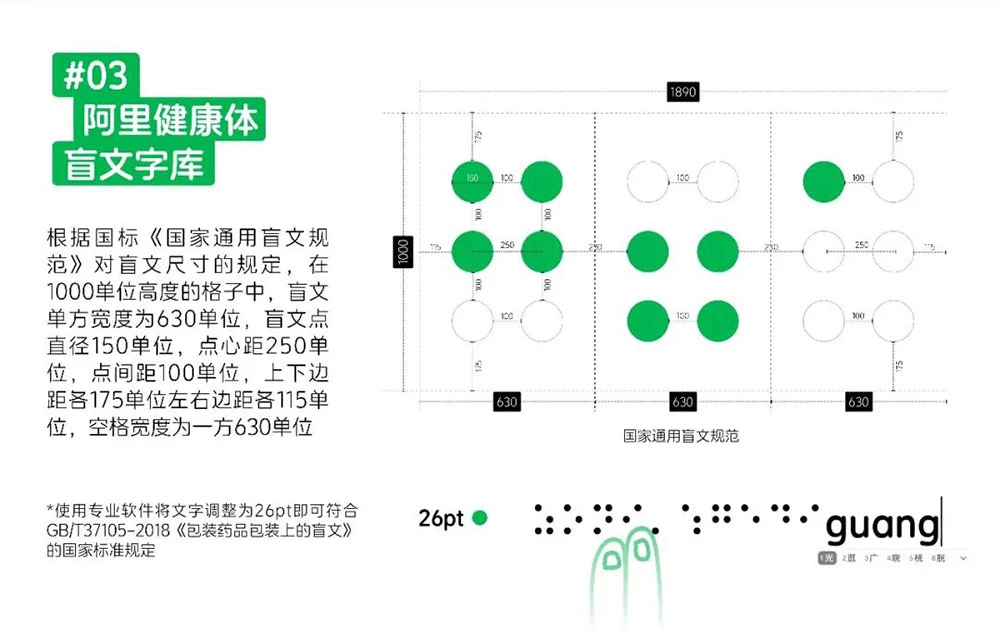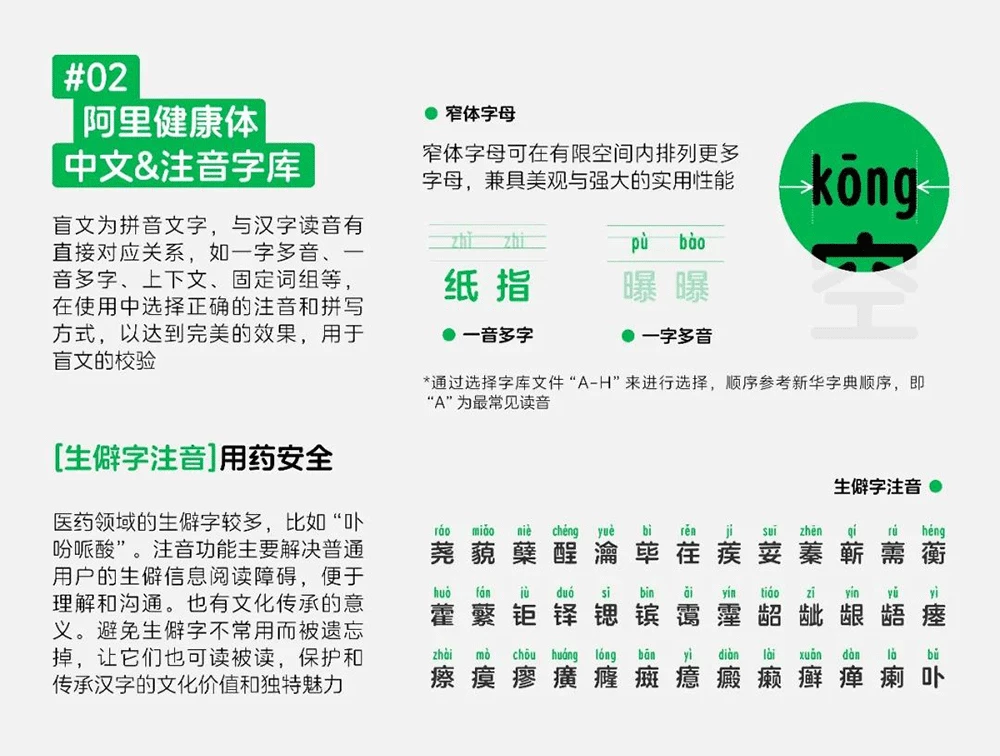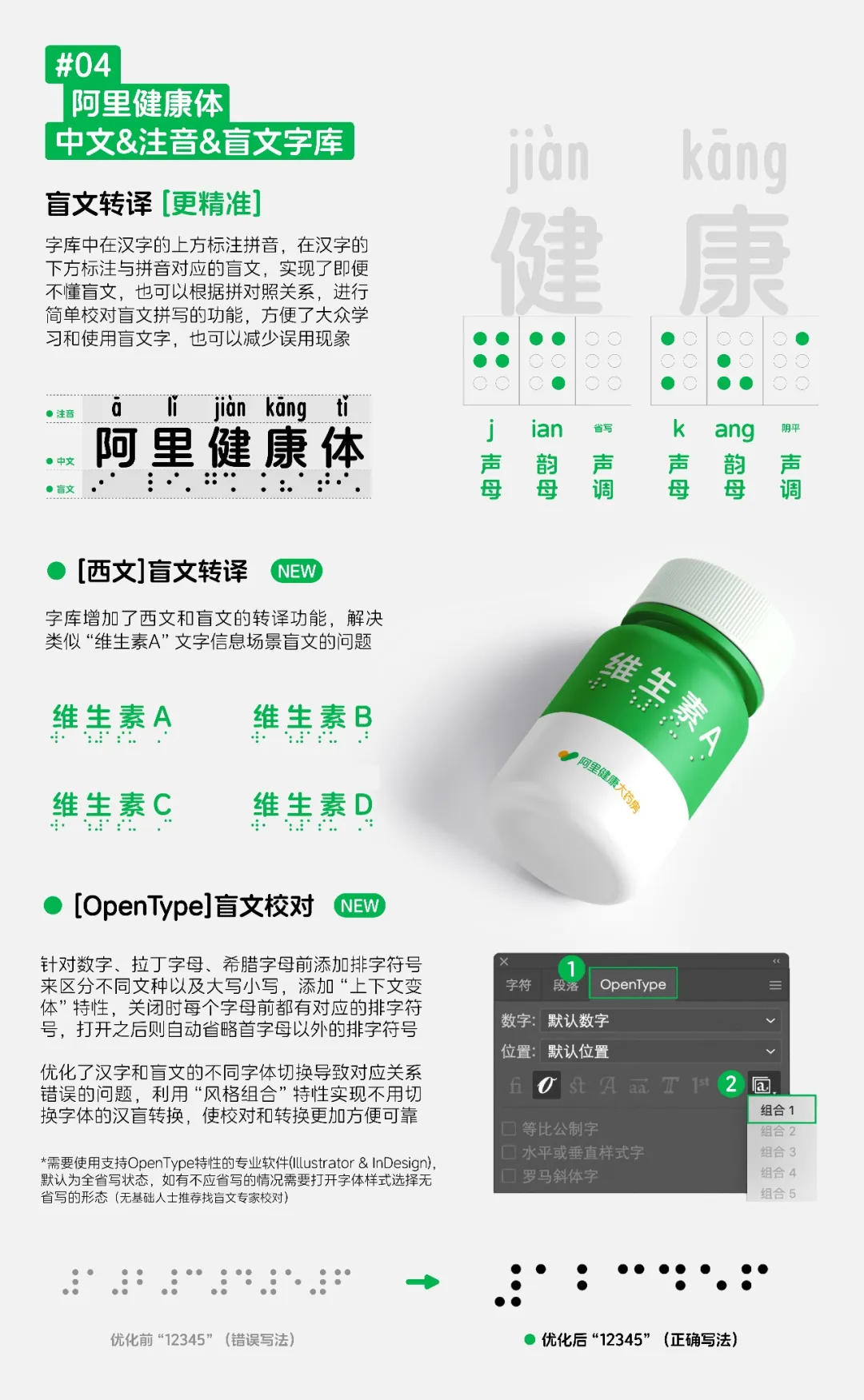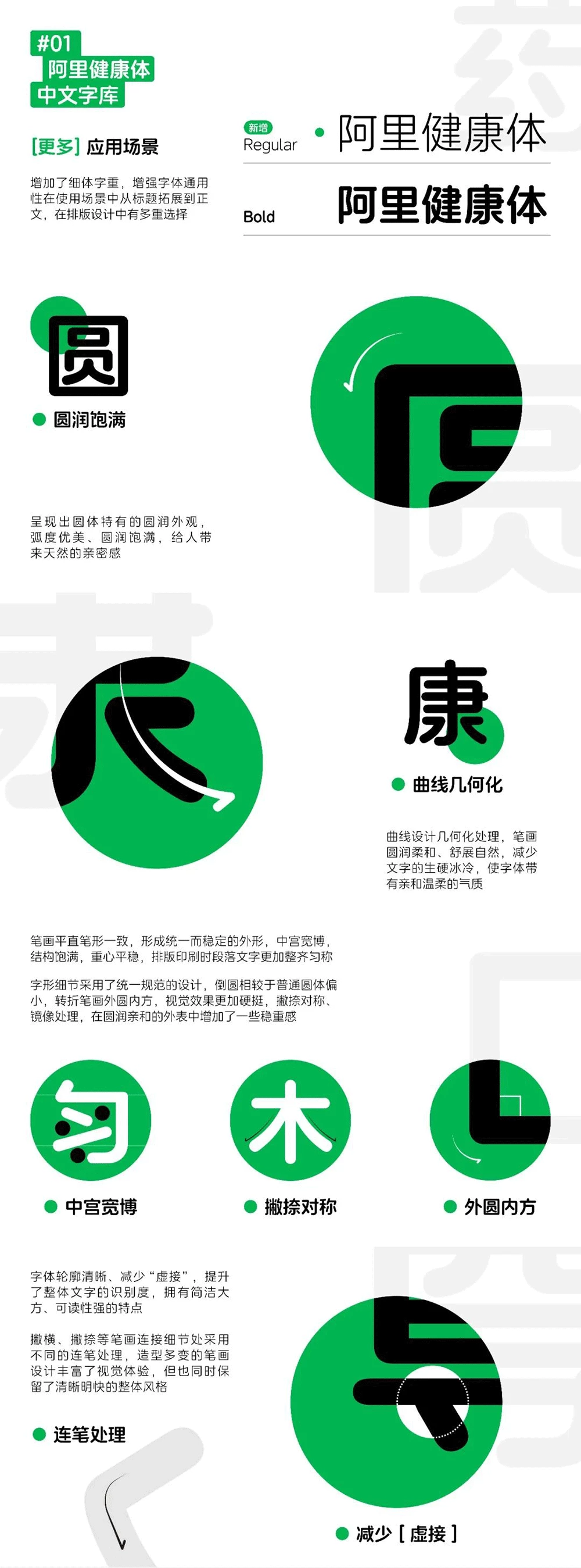
阿里健康体:国内首款服务于视障人士的中文盲文注音定制字体
阿里健康体是一款由方正字库与阿里健康合作开发的定制字体,是国内首款服务于视障人士的中文盲文注音定制字体,实现了中文汉字与盲文字符的串联与对应,方便视障人士识别和使用,笔画多以几何化处理方式,让字形看上去更加严谨端庄,字体具有圆润的外观,给人以温暖和亲和感,同时在笔画的转折处做了优化,以增强可读性和辨识度。